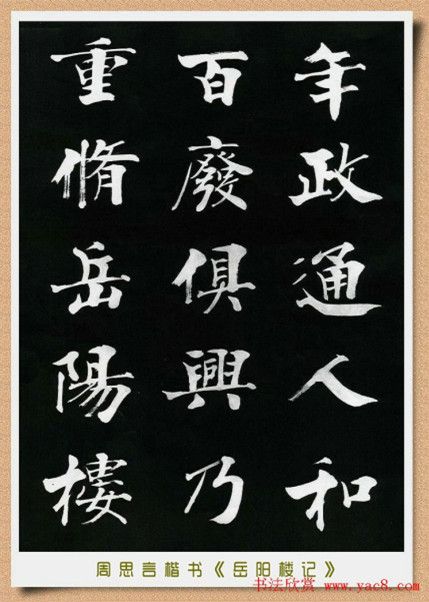
周思言,中国书法家协会会员,上海艺术进修学院教授,善楷书,尤擅小楷。其楷书以欧阳询、褚遂良、颜真卿为本,其作品用笔沉着精到,风格清俊、端庄,本字帖模板《岳阳楼记》为图片形式,共有24张,可通过百度网盘下载。
作品示例:
周思言的楷书名声在外,早在1993年,洛阳白马寺就收藏过他的对联;2008年11月,他应邀为温州千年古刹龙翔寺(始建于公元502年)书写“大雄宝殿”的门额,每字高宽均达120厘米,同时还为殿柱书写了一幅长联。
他的书法作品被诸多名流收藏,台湾著名漫画家蔡志忠先生在收藏了他的作品后,还专门赠他一幅漫画作纪念。